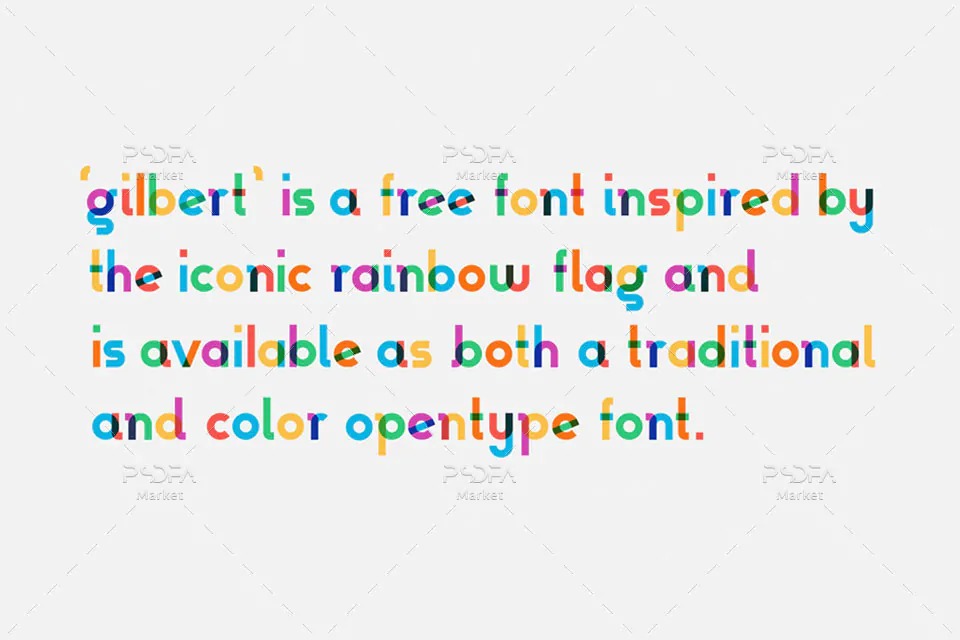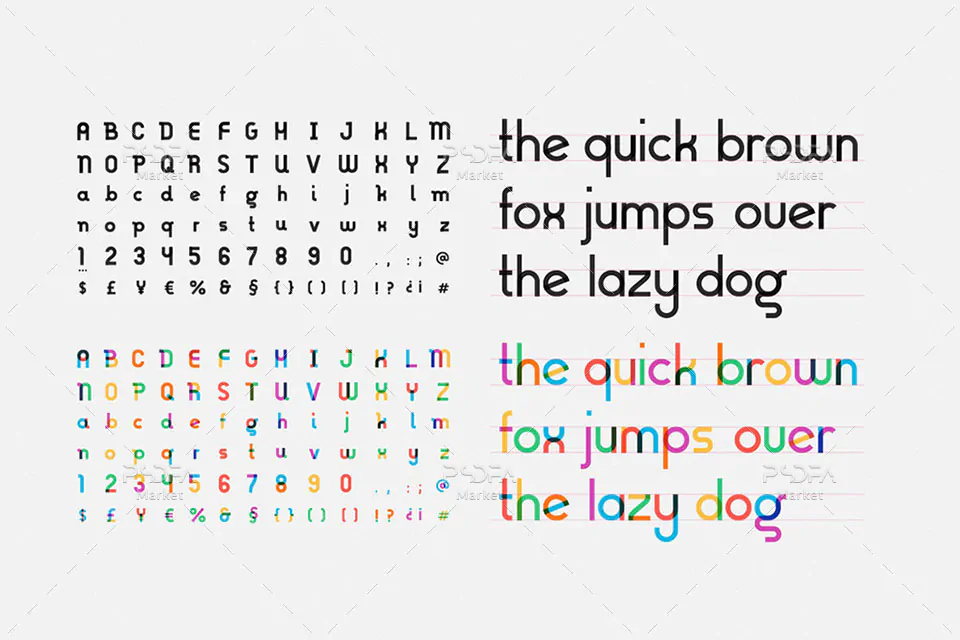
تایپوفیس رنگی Gilbert یک فونت و قلم برداری است که به صورت OpenType-SVG طراحی شده است و میتوانید از آن در نرمافزارهای فتوشاپ 2017، ایلاستریتور 2018 و ایندیزاین 2019 به بعد استفاده کنید. البته نسخه سبک و معمولی (بدون رنگ) این فونت زیبا نیز در فایل فشرده قرار دارد که میتوانید از آن در سایر نرمافزارهای ویرایشگر متن نیز استفاده کنید. در ضمن نسخه وب این فونت نیز در مجموعه قرار دارد که میتوانید از آن در طراحی وب هم استفاده نمائید.